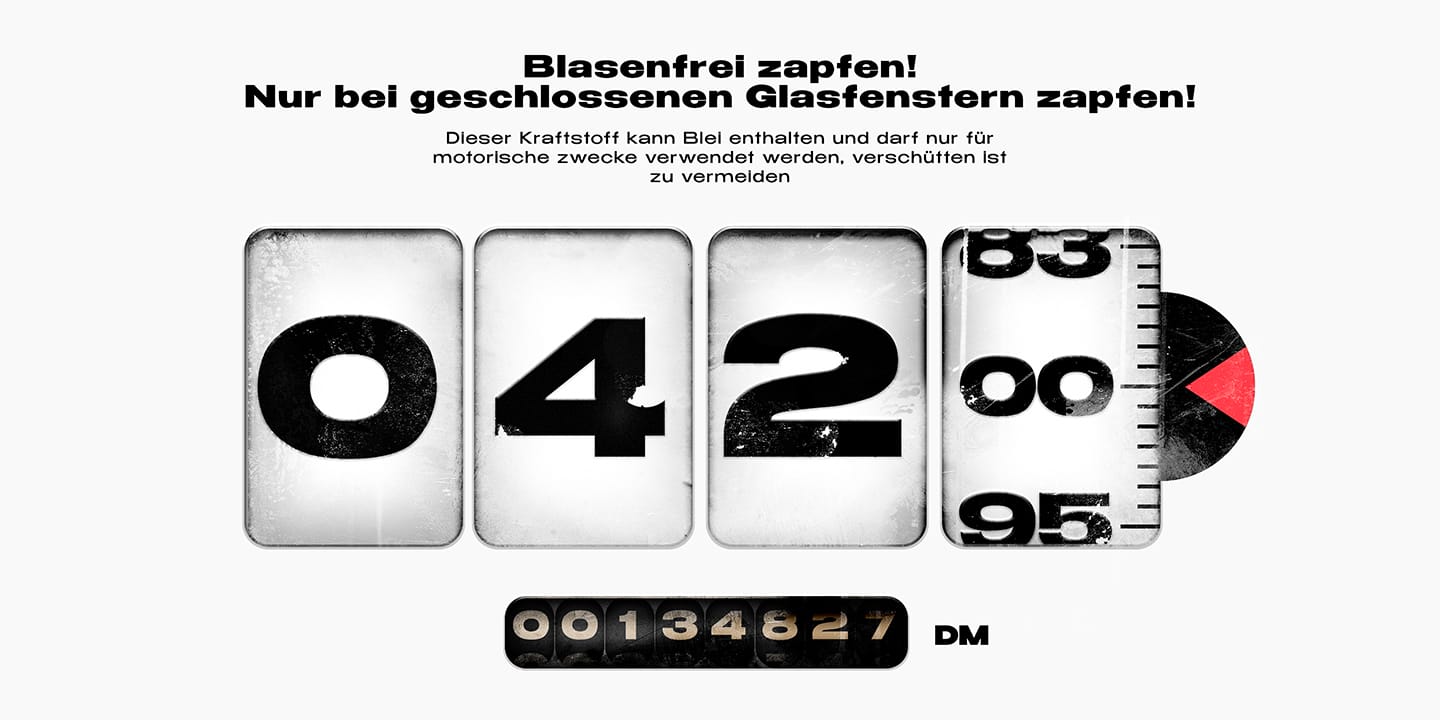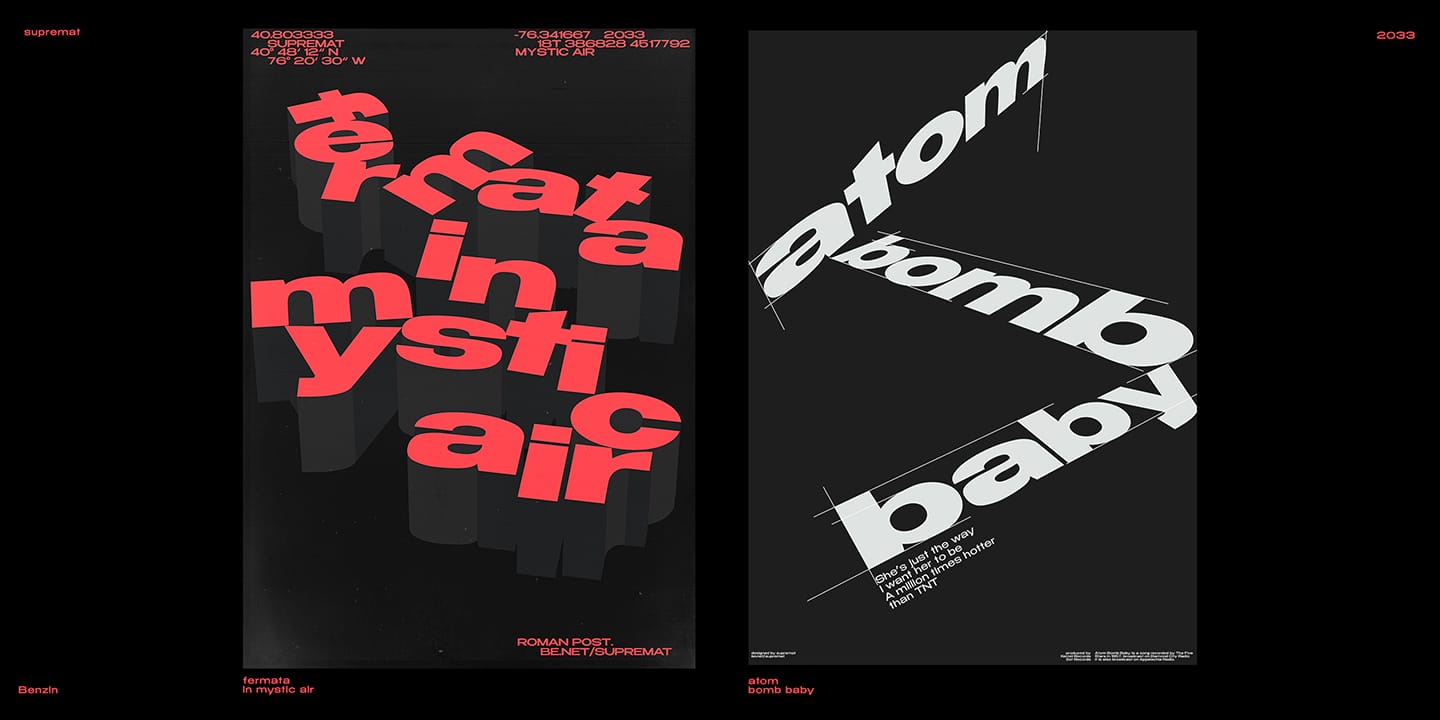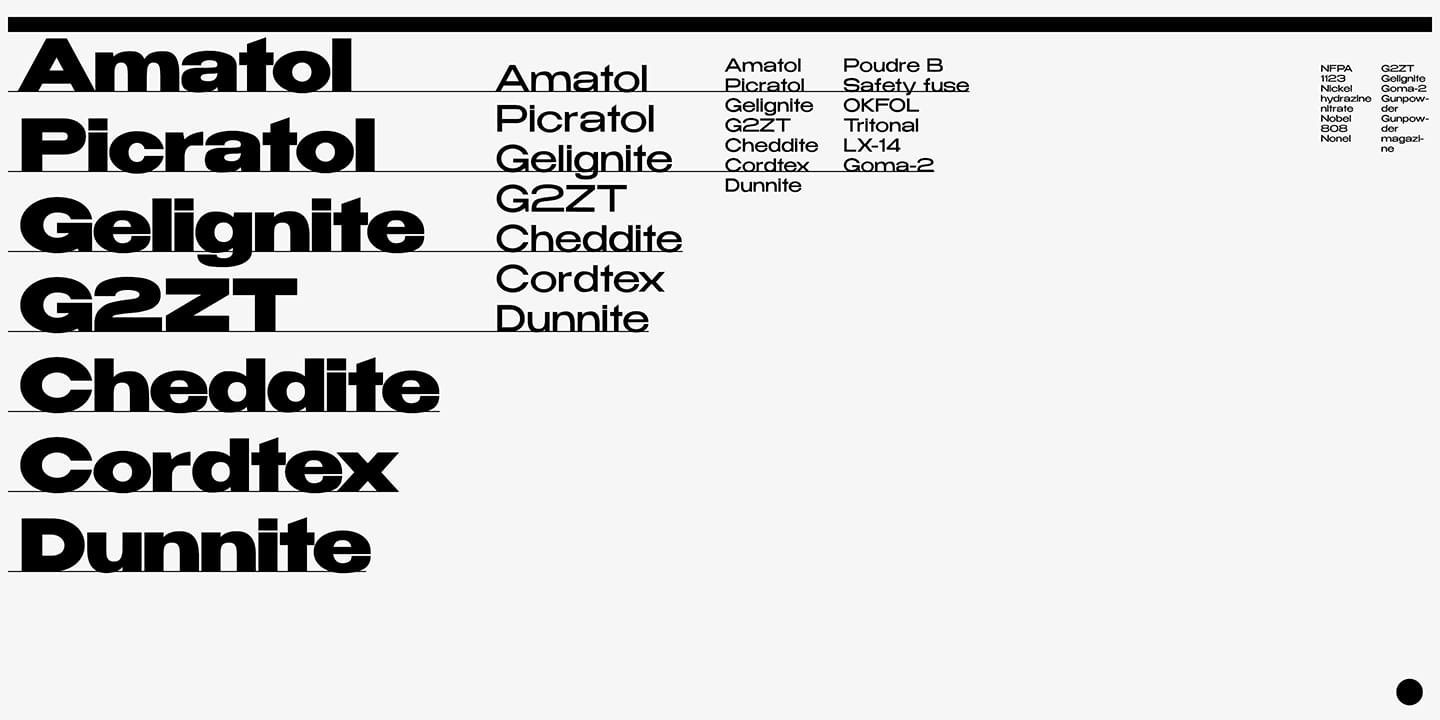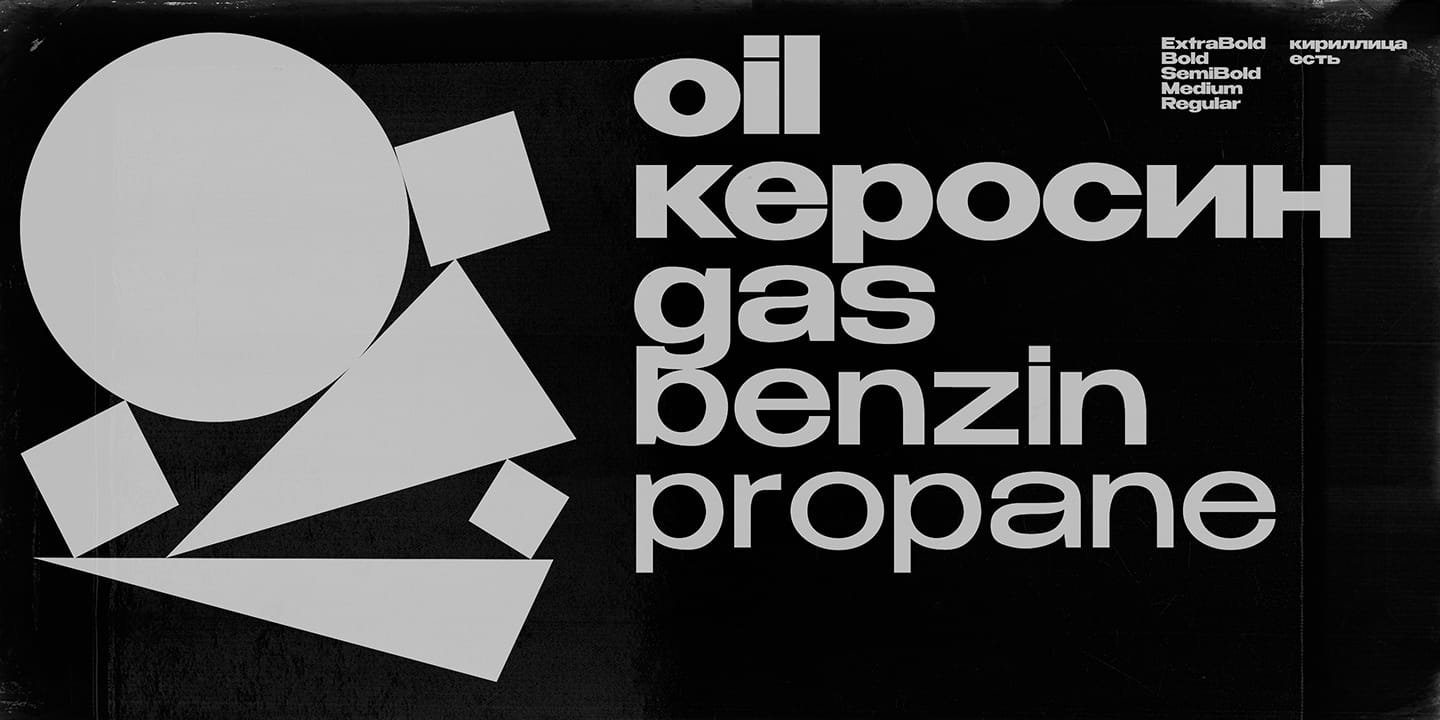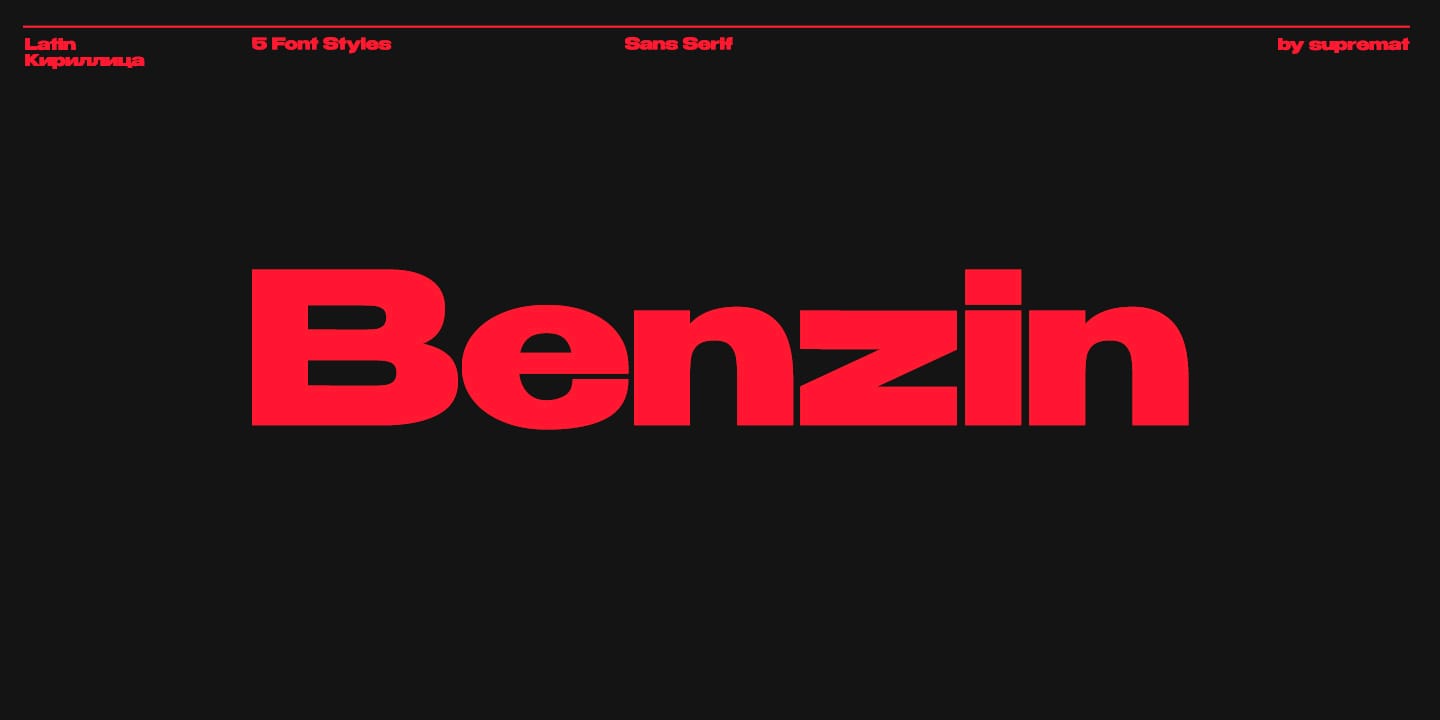
Benzin là một font sans serif hình học có 5 weight. Đây là một font chữ phổ biến có thể được sử dụng cho cả tiêu đề và đoạn văn, nhờ vào kerning tùy chỉnh cho phong cách đậm và mỏng. Ở kiểu mỏng, kerning thưa hơn, kiểu đậm thì dày hơn. Điều này cho phép bạn ngay lập tức sử dụng kiểu in đậm trong các dòng tiêu đề và áp phích lớn, và kiểu mảnh trong các văn bản và đoạn văn nhỏ. Điều này rất tiện lợi và bạn không cần phải suy nghĩ về việc thiết lập kerning.